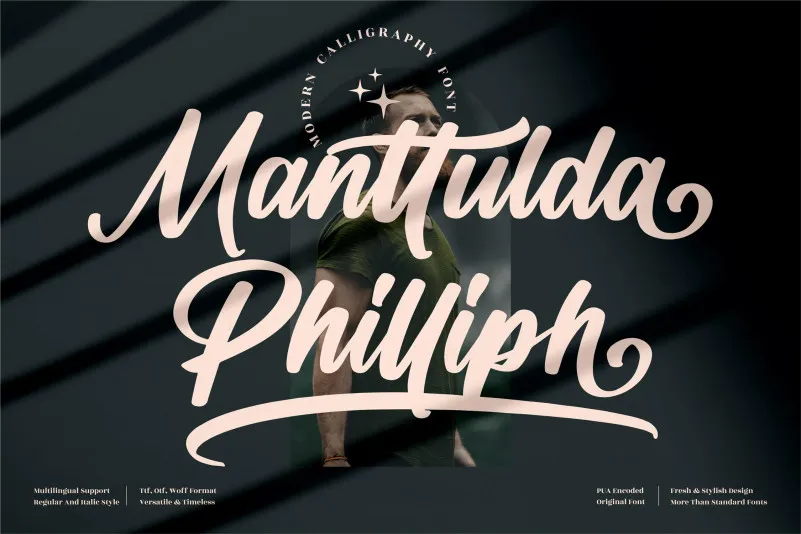
Manttulda Philliph Font – Download Grátis
A fonte “Manttulda Philliph” é perfeitamente adequada para qualquer projeto que exige um toque sofisticado. Ideal tanto para criações visuais complexas, como logos e design de produtos, quanto para ideias mais simples, como cartões de visita ou stickers personalizados. Sua versão script atraente é perfeita para aplicar uma aura de luxo em qualquer projeto que você esteja desenvolvendo, seja ele um pacote de produto sofisticado, etiquetas para alimentos orgânicos, cartazes publicitários ou até mesmo um convite de casamento. Essa fonte traz um toque de elegância e modernidade à sua proposta visual, garantindo que seus projetos apareçam imediatamente notáveis e premium. Seja para aqueles em quem você quer dar o sentimento certo de classe ou para criações onde desejar que a forma fale por si própria, é uma opção confiável para qualquer tipo de projeto.